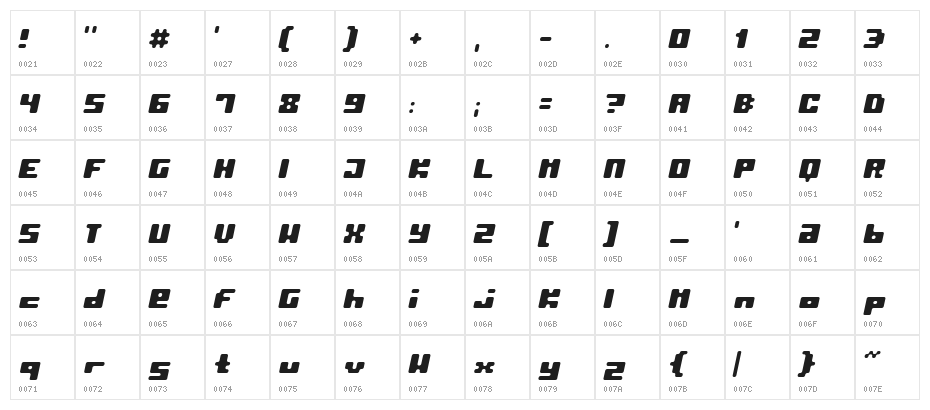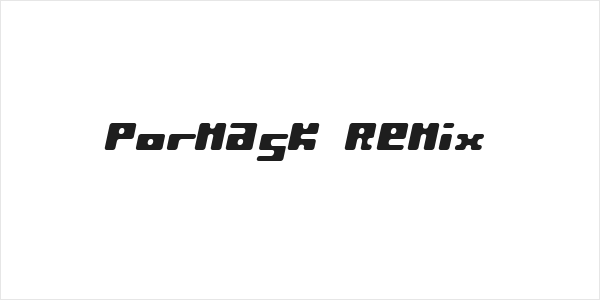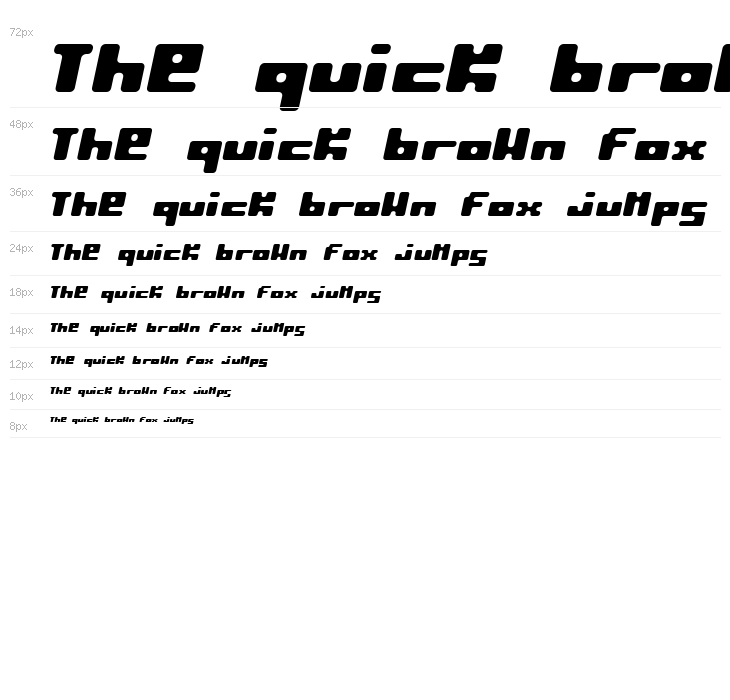
Pormask Remix Font
| Proiecte propuse | Ideal for sci-fi themed projects, video game titles, posters, and branding that requires a modern and bold aesthetic. |